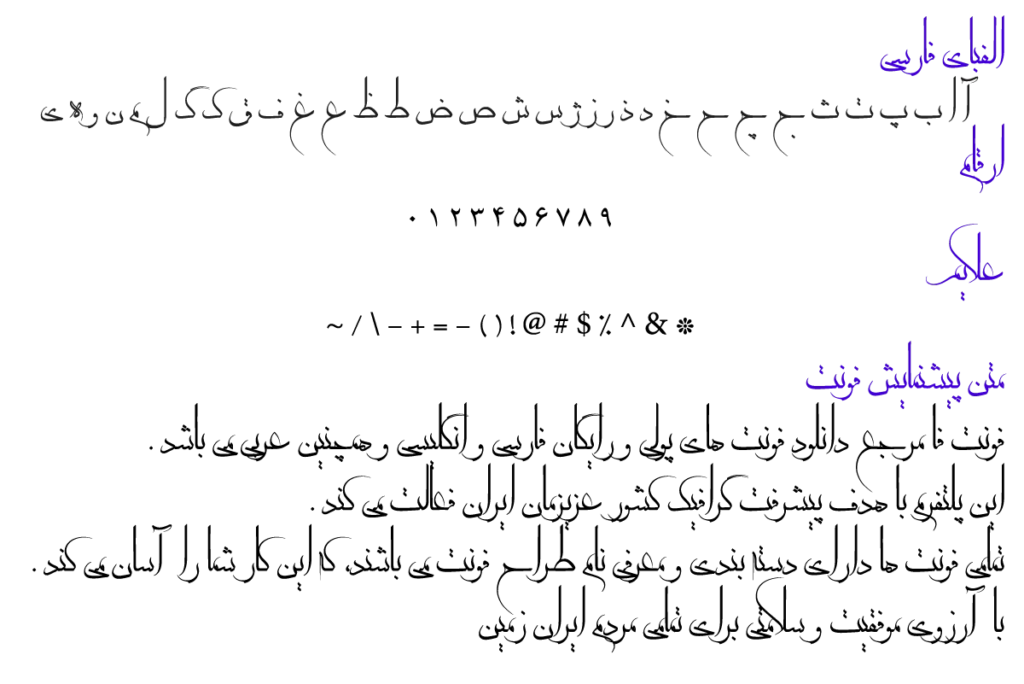
فونت فارسی زرقان معلی – ZARGHAN-MOALA
طراح فونت: ابراهیم شفیعی نوع فونت: فونت فانتزی
پیشنمایش فونت زرقان معلی
توضیحات و معرفی فونت زرقان معلی
فونت فارسی زرقان معلی ( ZARGHAN MOALA ) از مجموعه فونت های آزاد می باشد، همینطور نوع فونت فانتزی می باشد.
فونت زیبای مرتبط توسط ابراهیم شفیعی در سال 1398 طراحی و ساخته شده است.
در تصویر زیر می توانید شعر زیبای «وطنم» را که با این قلم نوشته شده، تماشا کنید.